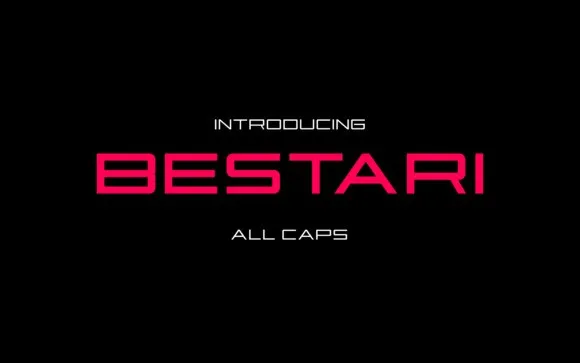
A fonte “Bestari Display Font” é uma nova tipografia sans serif inspirada por elementos modernos da atualidade. Seu design arredondado e dinâmico fazê-lo se destacar em qualquer projeto gráfico, seja ele uma publicação de moda ou um logotipo de empresa. Suas linhas leves e agradáveis ao olhar permitem que você dê vida aos seus designs, criando um impacto instantâneo e atraente. Seja você um designer profissional ou iniciante, “Bestari Display Font” é uma escolha perfeita para tornar seu trabalho ainda mais interessante e único. Adicione-o ao seu kit de ferramentas e observe como ele reforça sua personalidade criativa!